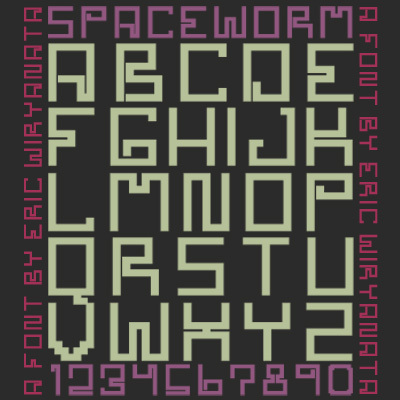
Spaceworm di Eric Wiryanata è un font pixel bitmap gratuito (solo maiuscole) con una solida estetica arcade e un pizzico di sci-fi. Le lettere sono costruite a partire da rigidi blocchi quadrati, ma le rotazioni a spirale e i tagli a gradino evitano che il design appaia statico, donando al set un ritmo labirintico che si sposa perfettamente con la cultura dei giochi retrò.
È ideale ovunque tu voglia un look digitale con carattere: loghi di giochi, titoli di poster, grafiche per stream, fanzine e cartelli grafici. Usalo per titoli brevi, copertine o monogrammi, dove le forme squadrate e gli angoli curvi riescono a comunicare immediatamente.
Space Worm... ho semplicemente pensato che il nome si adattasse bene al font. Include più simboli; controlla tutti i caratteri disponibili tramite la Mappa caratteri del tuo sistema.